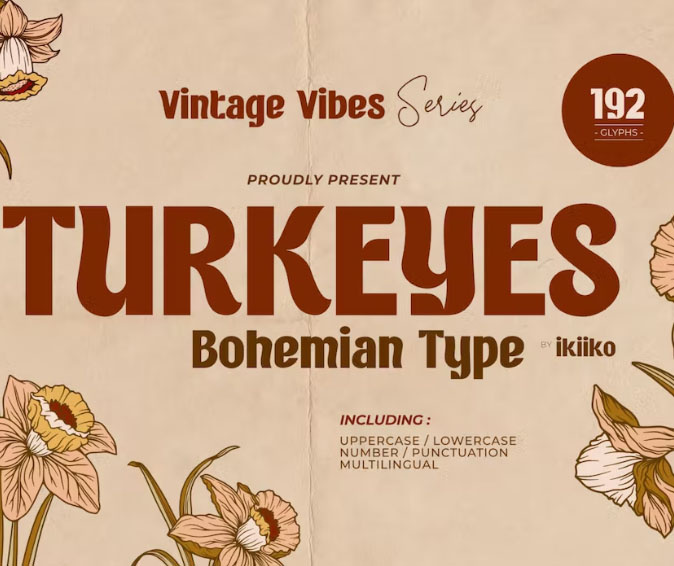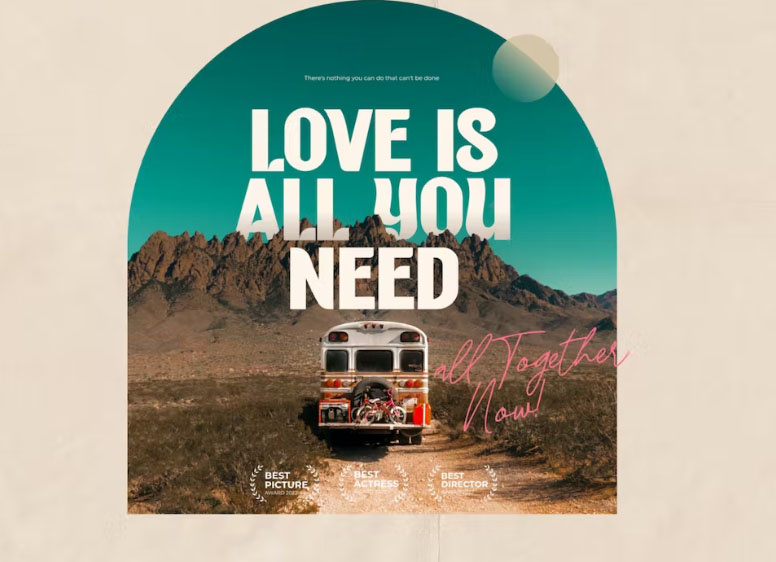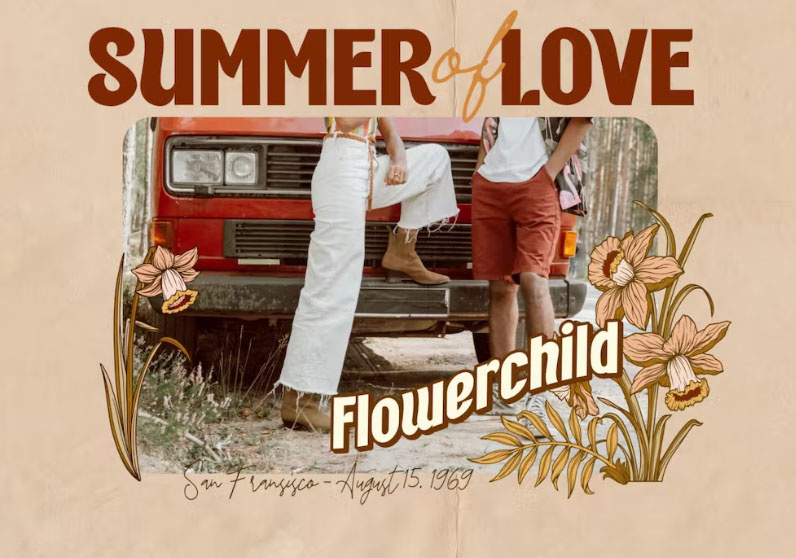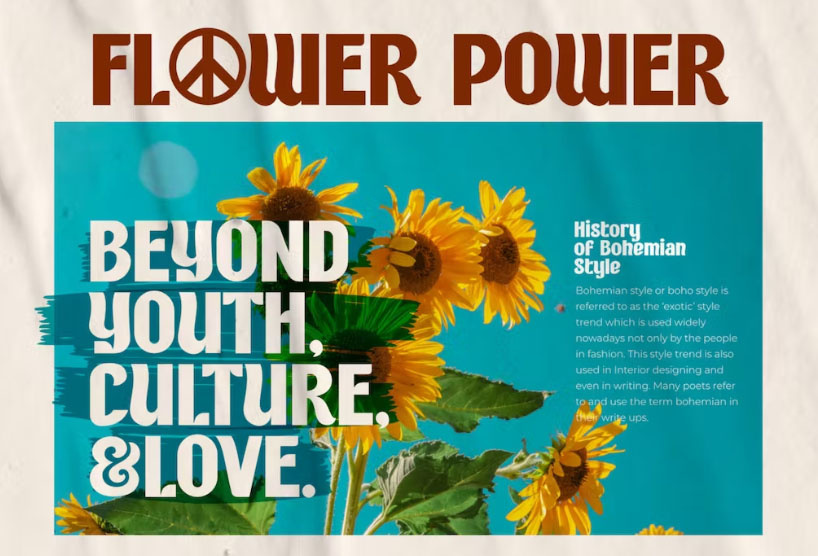
یک فونت جذاب به سبک بوهو یک فونت قدیمی است که هم ظاهر مدرن و هم کلاسیک و قدیمی دارد. دانلود فونت به سبک بوهو Turkeyes از دوران بوهمی الهام گرفته شده است، فونت مناسب برای ایجاد طرح بندی در دهه 60 یا 70. این فونت شکل منحصربه‌فردی دارد که می‌تواند به لوگوی برند، پوستر، غذا و نوشیدنی‌ها و پروژه‌های دیگر ظاهری منحصربه‌فرد یا قدیمی بدهد. برای مشاهده پیش نمایش هایی از این فونت انگلیسی بوهو از جی اف ایکس دانلود به ادامه مطلب مراجعه کنید.
• نام فونت: Turkeyes - Bohemian Type
• حروف بزرگ و کوچک
• شماره و نقطه گذاری
• پشتیبانی چند زبانه